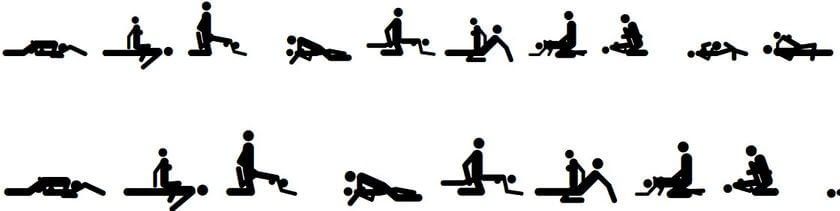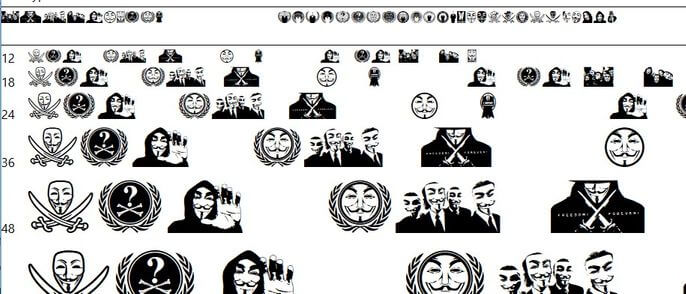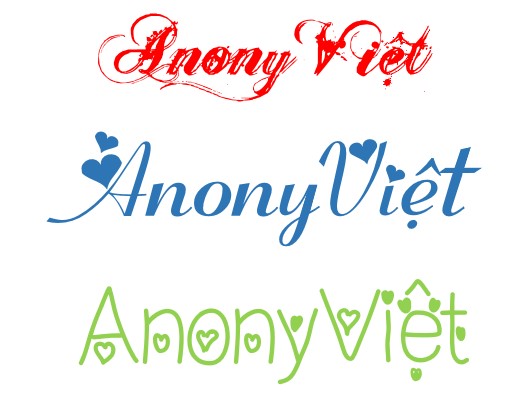
Font PicsArt Việt Hóa dùng để ghi chữ lên hình tuyệt đẹp
Việc sử dụng các app trên điện thoại để chỉnh sửa ảnh không còn xa lạ. Đa số mọi người sử dụng PicsArt để chèn chữ vào ảnh. Nhưng hiện nay Font PicsArt Việt Hóa rất ít, các bạn gặp phải tình trạng số 1 chữ có dấu sẽ bị lỗi Font. Hôm nay mình sẽ chia sẻ bạn bộ Font kiểu cực đẹp thường được dùng để chỉnh sửa trên điện thoại.
Font PicArt Việt hóa hổ trợ đủ chuẩn tiếng Việt, gõ dấu không bị lỗi. Đặc biệt bộ Font này dành cho những bạn thích lãng mạng, hoặc hoài niệm. Bộ font bao gồm những nét chữ có trái tim trong đó. Gọi chung là Font trái tim.
font trái tim
Một số font về hình ảnh như: font troller, font anonymouse, font 40 tư thế xxx….
Tên font: Anonbats
Tên font: 40ways
Đây là bộ Font Việt Hóa dùng để ghi hình lên chữ. AnonyViet đã lọc ra những Font đẹp nhất để chia sẻ cho các bạn. Trong đó mình thích nhất là các Font trái tim dùng để làm thiệp tặng bạn gái.
Bộ font này có hỗ trợ đầy đủ tiếng Việt không?
Có, bộ Font PicsArt Việt Hóa hỗ trợ đầy đủ tiếng Việt, đảm bảo gõ dấu không bị lỗi.